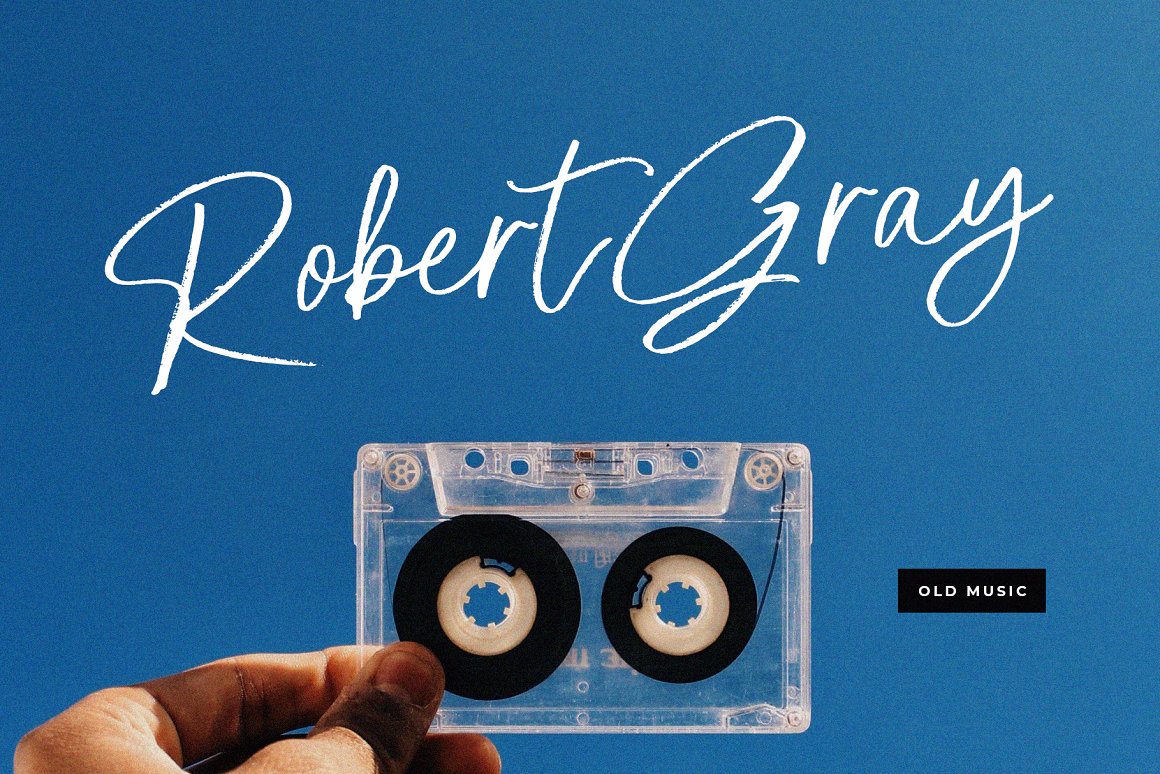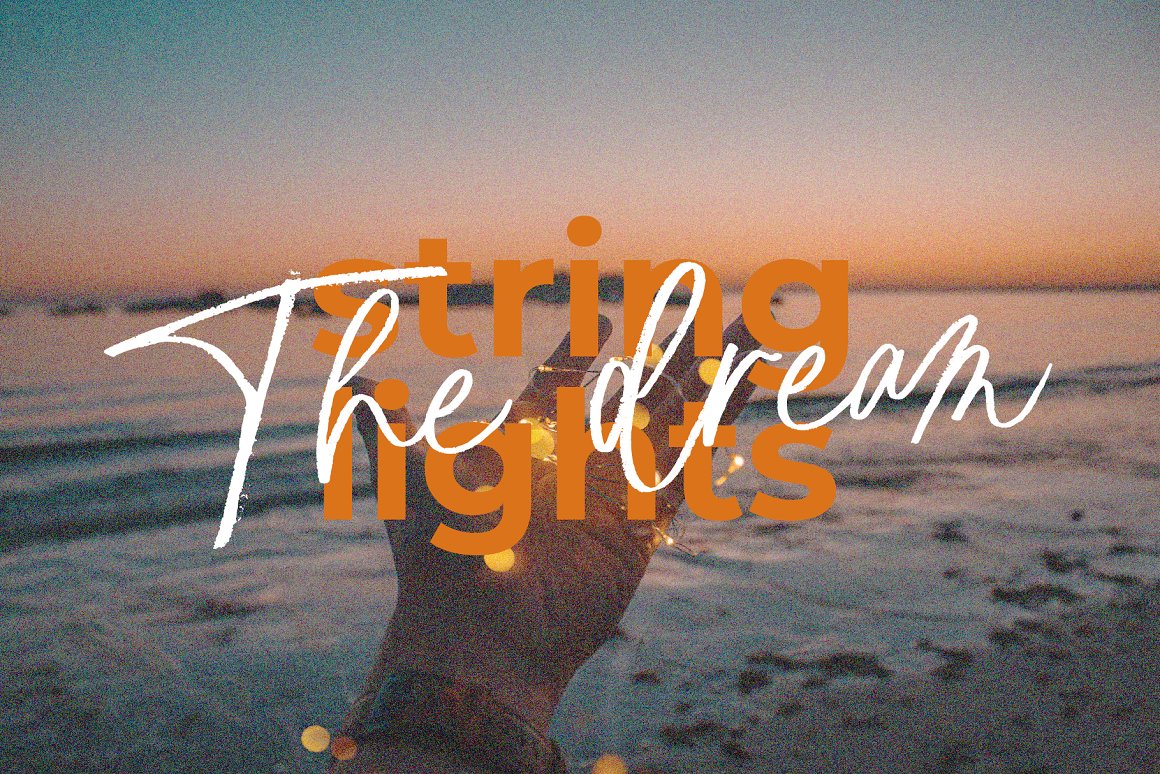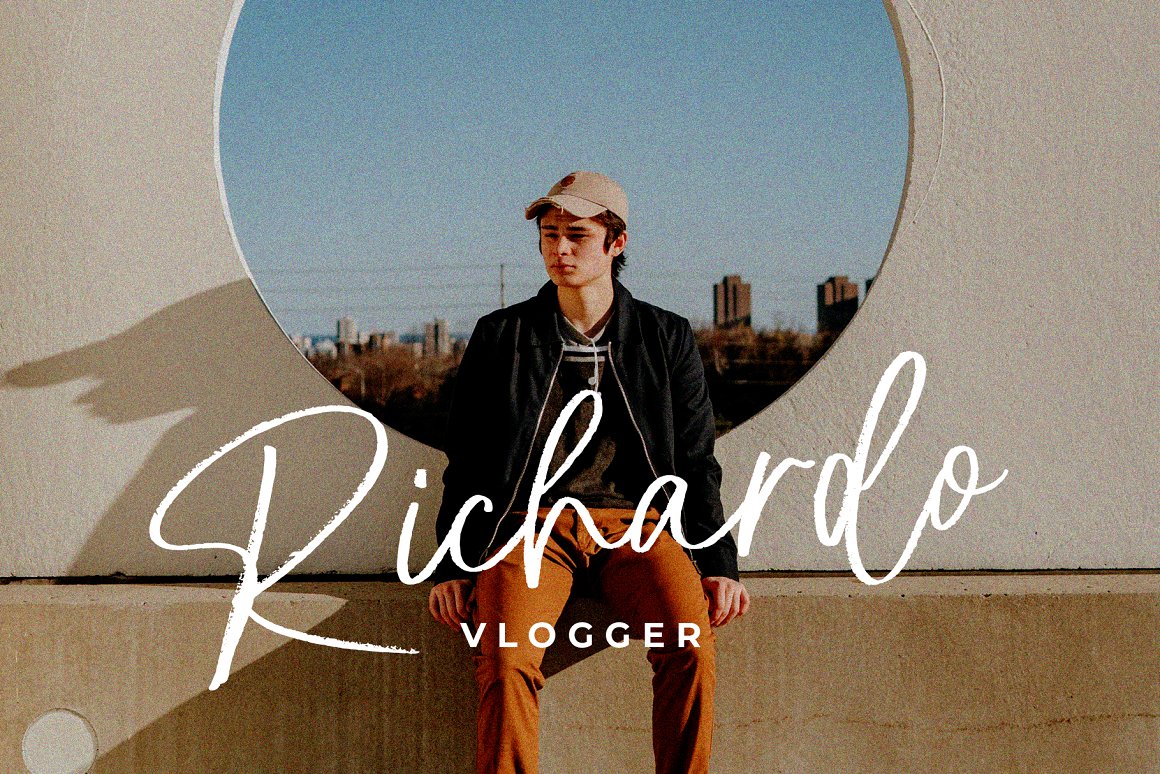
Protan Sheyom Brush Font
Description de Protan Sheyom Brush Font
Protan Sheyom est une police qui a été grattée avec un stylo pinceau, pour obtenir une texture naturelle, cette police montrera les caractéristiques de la main. Cette police est parfaite pour divers endroits tels que les vêtements, les affiches, les livres de titres, les conceptions de papeterie, les citations, les marques, les logos, les invitations, les cartes de vœux, les t-shirts, les conceptions d’emballage et plus encore.